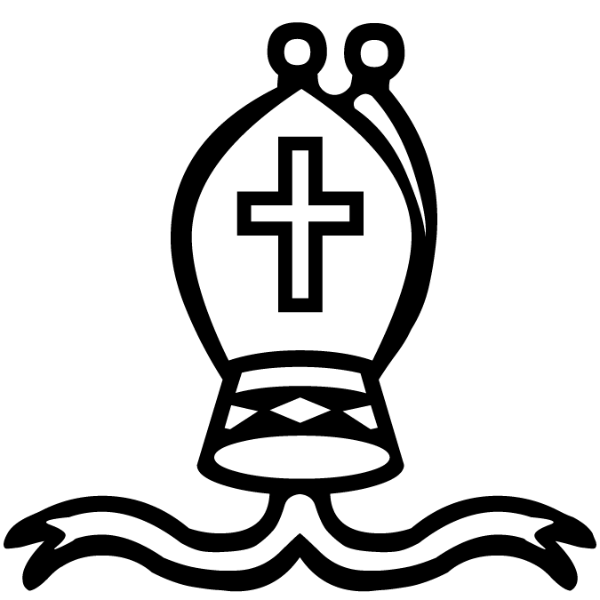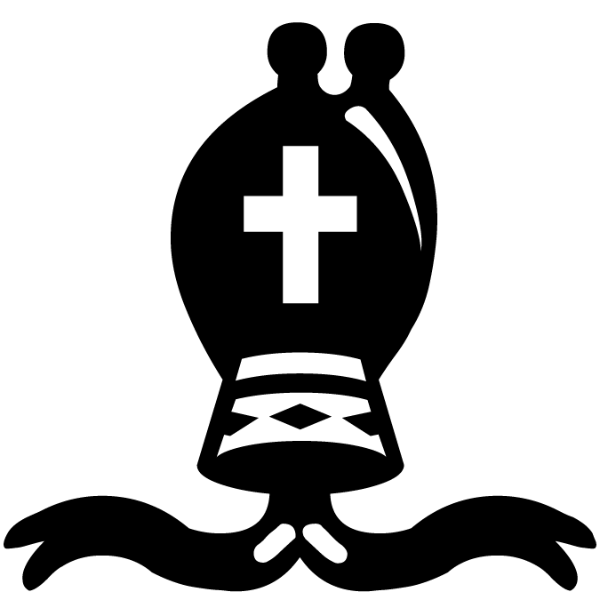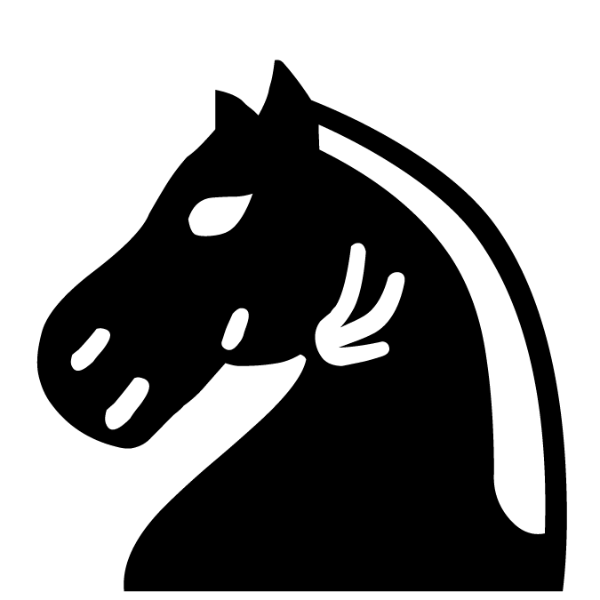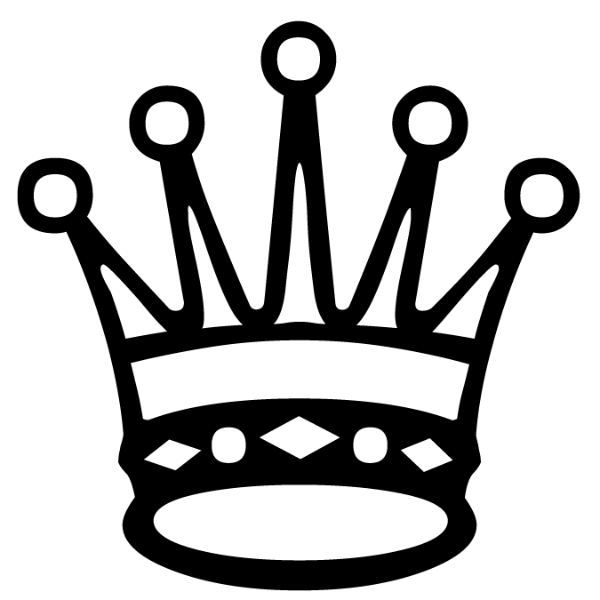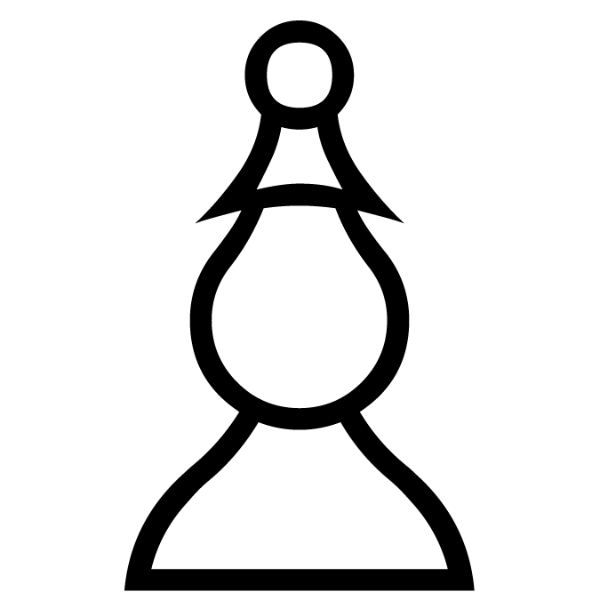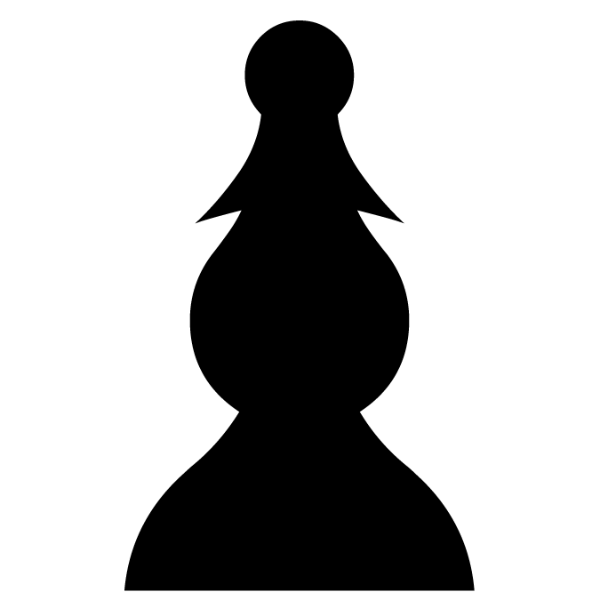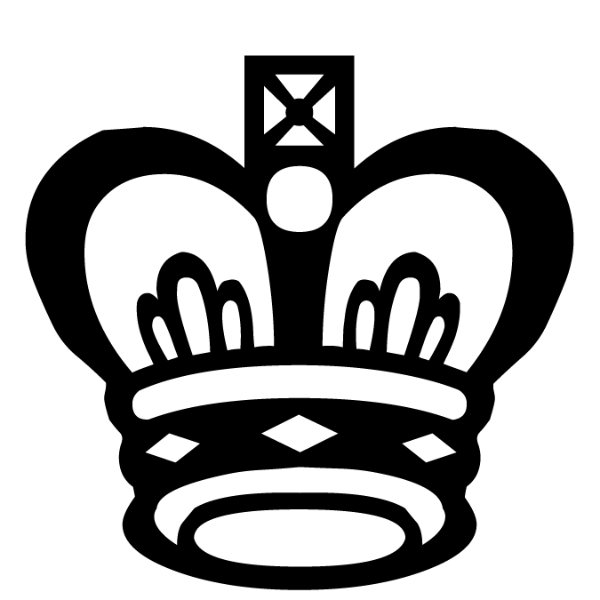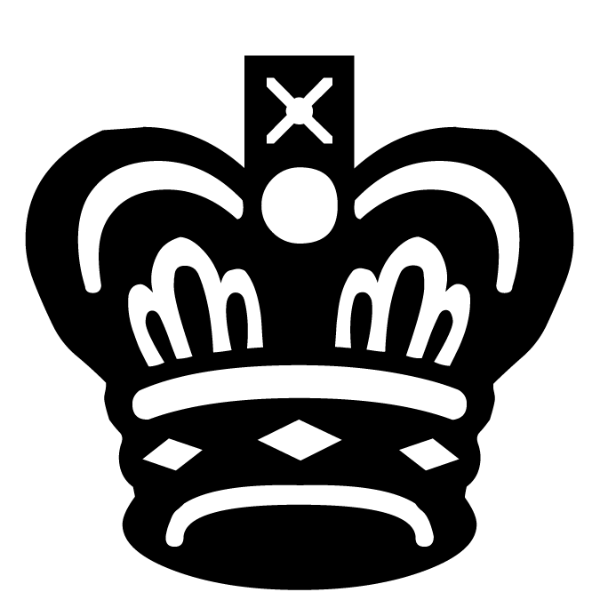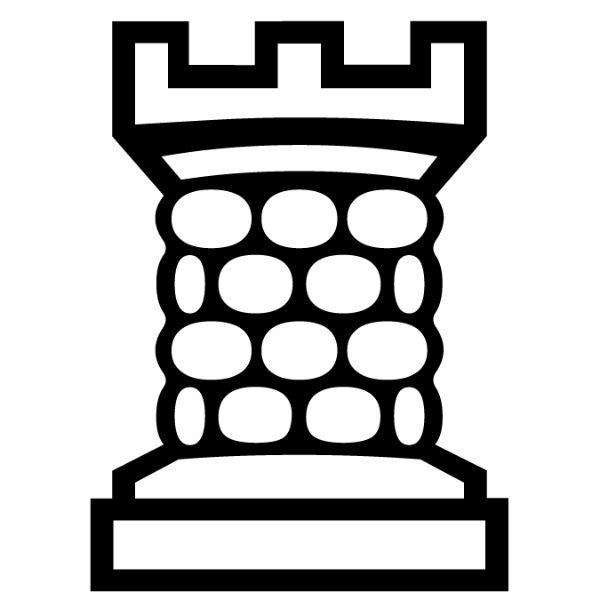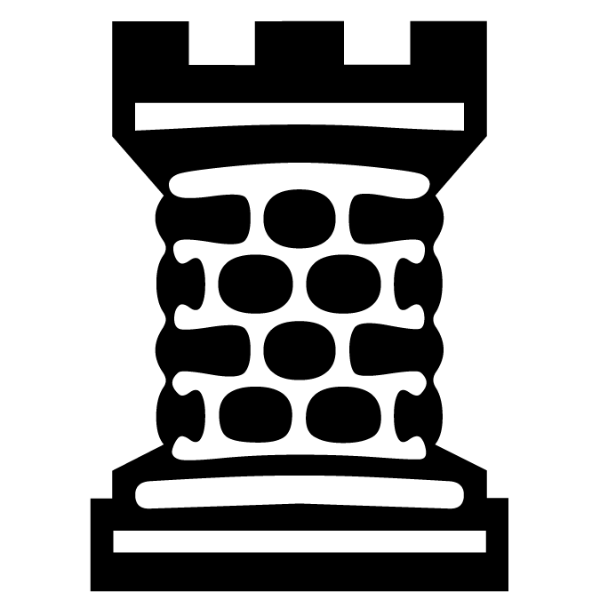
Fuente de Ajedrez Chess Leipzig – Este font combina sofisticación y elegancia, convirtiéndose en una de las opciones más destacadas para amantes del ajedrez y diseñadores. Chess Leipzig es una Fuente Freeware diseñada por Armando Hernandez Marroquin, ideal para proyectos que requieren claridad y estética. Puedes descargarla e instalarla fácilmente en tu ordenador. A continuación, puedes ver imágenes de muestra y acceder al enlace de descarga.